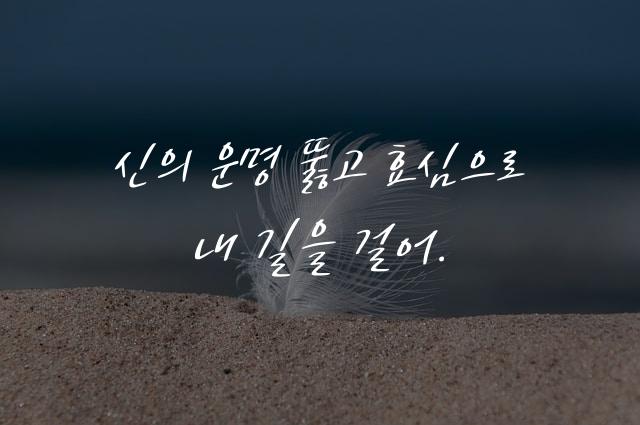
문래러는 상상토끼에서 제작한 한국어 폰트로, 삐뚤빼뚤한 선의 감성을 담아 유니크한 디자인을 선보입니다. 간결하면서도 개성 있는 스타일로 시각적 흥미를 제공합니다.
문래러은(는)
계열의 생김새를 가지고 있으며
로고 디자인, 포스터, 광고 캠페인 등에서 자주 활용되며, 효과적인 메시지 전달에 적합합니다.
이 폰트는 광고/마케팅, 크리에이티브, 문화/예술 분야에 잘 어울리며,
감성적인, 세련된, 창의적인 느낌을 담고 있는 것이 특징입니다.